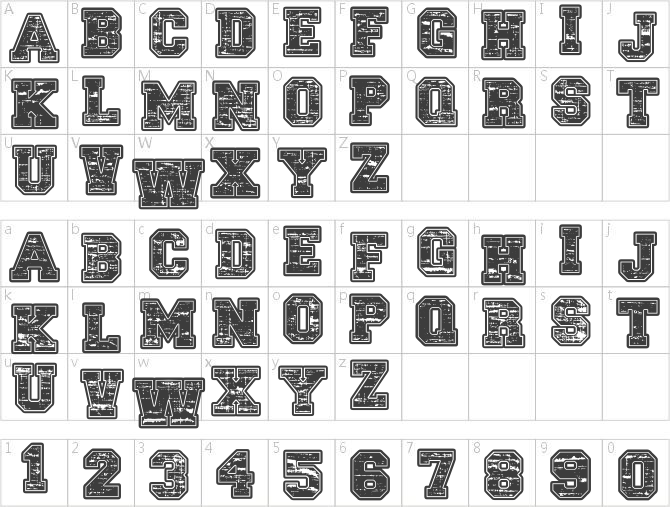
Lethal League 詳情頁(yè)
Lethal League字體字庫(kù)是一款讓人賞心悅目、百看不厭的英文字體,適合各類廣告和產(chǎn)品包裝設(shè)計(jì)應(yīng)用,字體大小0.23MB,格式為ttf字體,上傳用戶是/zyj【GF】,作者/版權(quán)方為未知